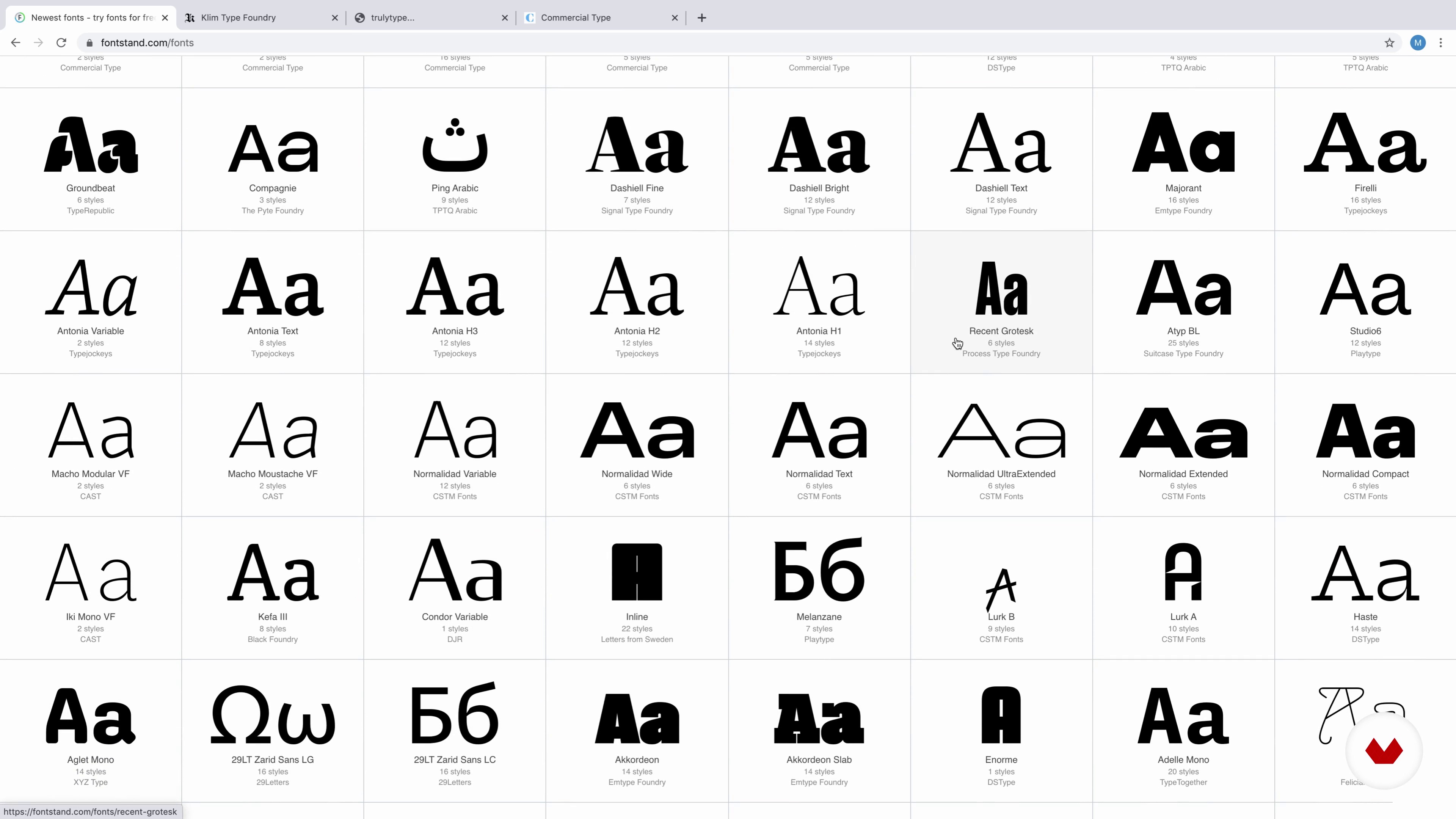
Typographie
À propos de la leçon : Typographie
“C'est maintenant le temps de la typographie. Nous allons faire une classification typologique complète des grands groupes typographiques qui existent et nous parlerons des caractéristiques qui les différencient. Je vais vous donner quelques conseils pour faire une sélection de police correcte et comment combiner correctement différentes polices. Enfin, nous ferons un tour des différentes fonderies de types, analysant ce que chacune d'elles peut apporter et montrant leurs catalogues de polices. Bien que dans ce cours nous n'allons pas approfondir la typographie en tant que telle, nous allons passer en revue des notions de base telles que sa classification, et voir quelques fonderies où acheter des polices de qualité pour notre projet. ”
“Typographie Dans cette leçon, je parlerai de la typographie. Nous passerons en revue l'histoire de la typographie, s'arrêter à sa classification typologique, nous verrons comment combiner correctement la typographie et enfin, nous donnerons un aperçu de certaines fonderies de types. Fonce. Nous ferons une classification typologique complète des grands groupes typographiques et nous parlerons des gammes qui le différencient. Je vais vous donner quelques indications pour faire une sélection typographique correcte et comment combiner correctement différentes polices. Bien que dans ce cours, no...”